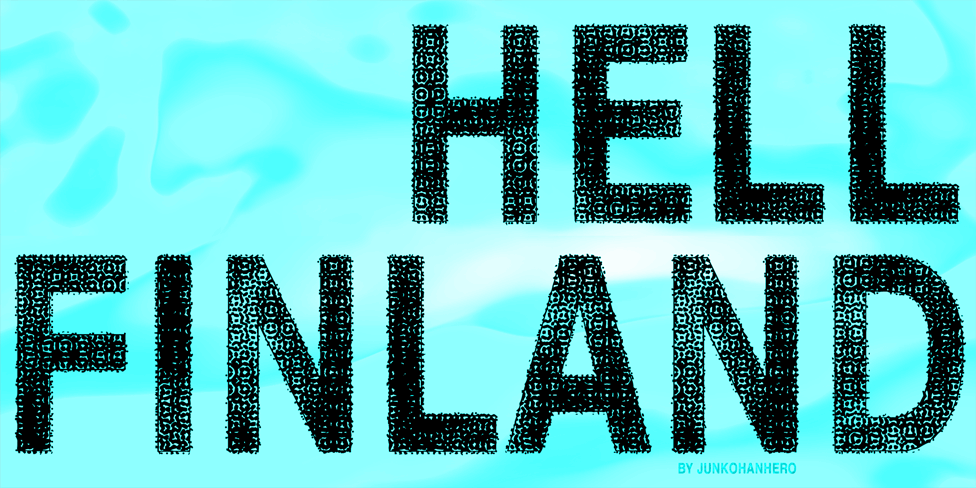
A fonte Hell Finland é uma escolha perfeita para projetos decorativos e criativos. Desenvolvida pelo designer Hamilton, esta fonte traz elementos únicos e modernos que são ideais para ilustrações de cartões personalizados ou design gráfico imprimível. Se você está procurando por algo novo e inovador, Hell Finland é uma ótima opção. Esse é um projeto gratuito personalizado para uso pessoal, mas se você quiser usar a fonte em um trabalho comercial, basta entrar em contato com o designer Hamilton através do PayPal. Ele aceita pagamentos de 15 euros ou 20 dólares americanos por licença comercial. Após realizar o pagamento, é só mandar um e-mail para receber todas as informações necessárias. Além disso, se você achar que Hell Finland merece um lugar na sua coleção pessoal de fontes, considere fazer uma doação regular. Hamilton valoriza contribuições voluntárias e pode ser uma maneira gratificante de apoiar seu trabalho enquanto ainda recebe benefícios de ter acesso adicional às suas obras. Se você busca uma fonte que complementará perfeitamente qualquer projeto decorativo que realize, Hell Finland é uma excelente escolha.